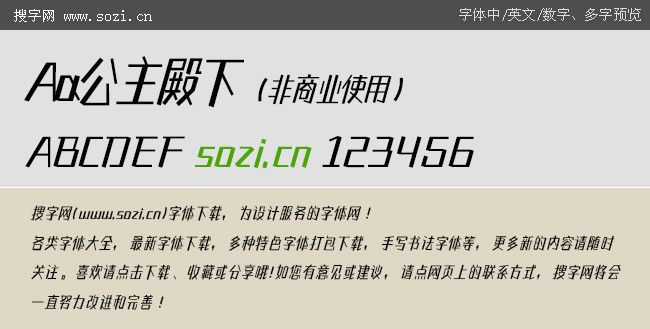
Aa公主殿下
搜字網(wǎng)給大家提供一款A(yù)a公主殿下(非商業(yè)使用)中文字體下載,該字體是一款可愛(ài)標(biāo)題藝術(shù)字體,字體筆觸適中,字形端正排版略顯傾斜,清新簡(jiǎn)明。適合書(shū)裝設(shè)計(jì)、包裝設(shè)計(jì)、海報(bào)設(shè)計(jì)等應(yīng)用(此字體為個(gè)人非商用版,商用可以聯(lián)系QQ:1006760504)。